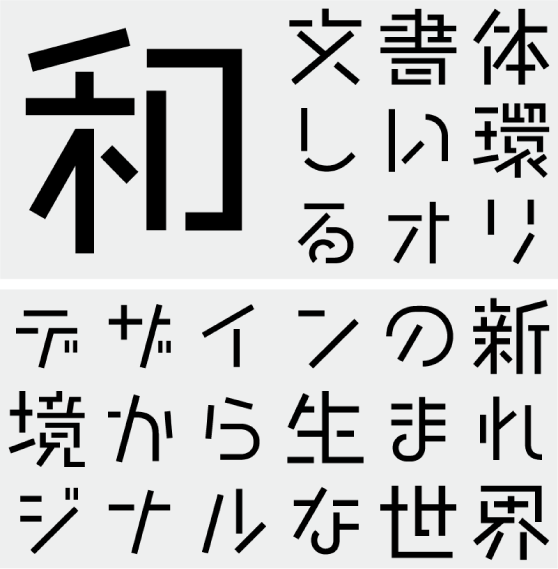
F1000-ネオステンシル F2 Regular (Yukichi Takada)
F1000-NeoStencilF2-Regular
和文にステンシル書体がないことから、和文を含めた新しいステンシル書体を制作。画数の多い字種の漢字では、交差する線の省略などで、元の字形のイメージを保ちながら可読性を確保した。